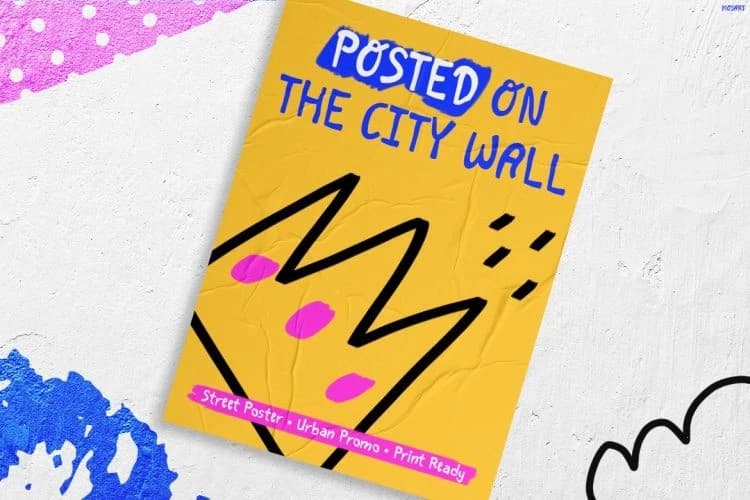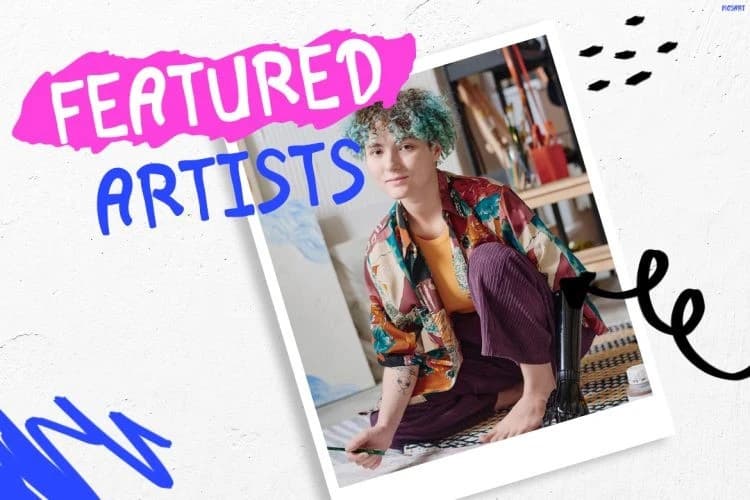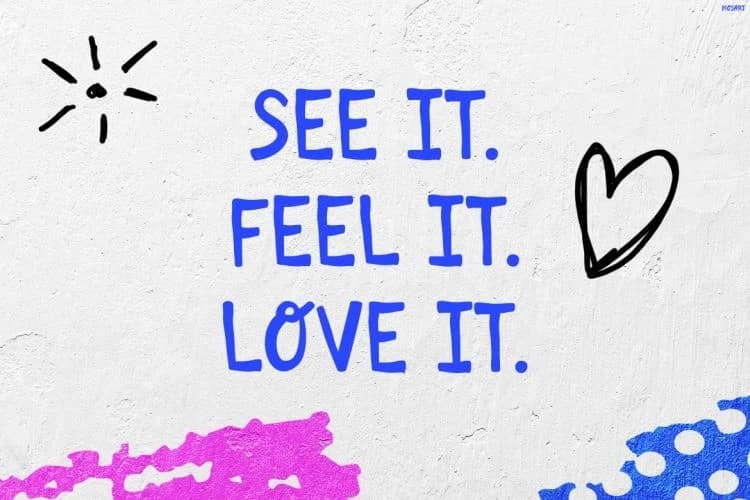
Mosart Neşeli Yazı Tipi
Mosart Playful Font, sokak sanatı, karalama kültürü ve oyuncu şehir yaratıcılığından ilham alan cesur ve ifade gücü yüksek bir el yazısı gösterim fontudur. Enerjik vuruşlar, kusurlu çizgiler ve sanatsal grafiti tarzı detaylarla tasarlanmıştır; bu font anında eğlence yaratır.
Mosart Playful Font, sokak sanatı, karalama kültürü ve oyunbaz kentsel yaratıcılıktan ilham alan cesur ve ifade gücü yüksek bir el yazısı gösterim yazı tipidir. Enerjik çizgiler, kusurlu hatlar ve sanatsal grafiti tarzı detaylarla tasarlanmıştır; bu yazı tipi anında eğlence yaratır